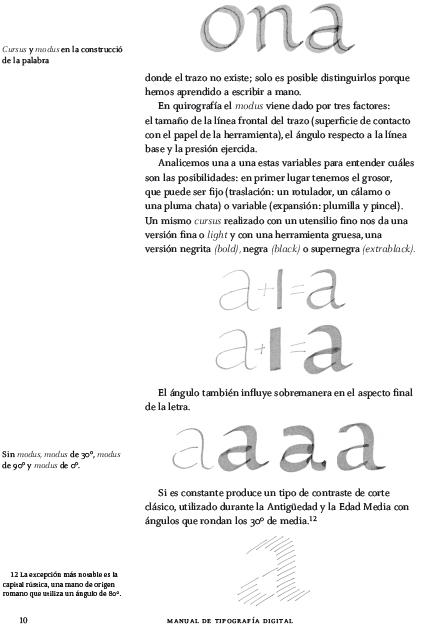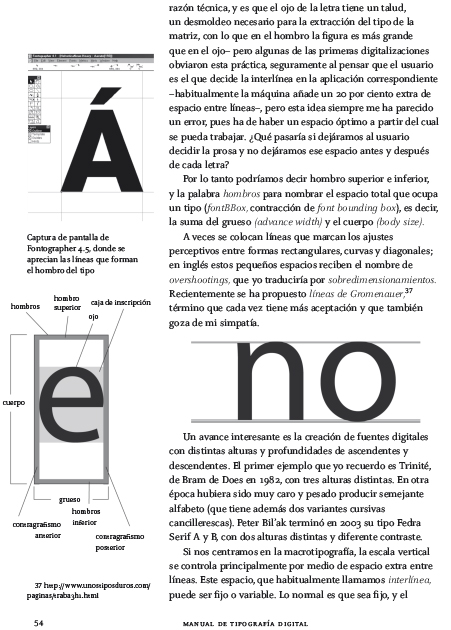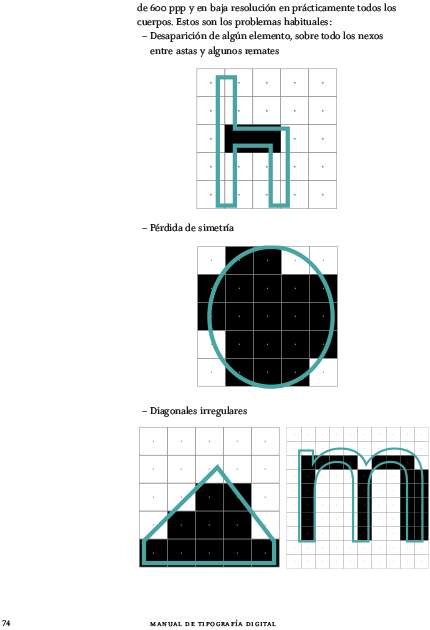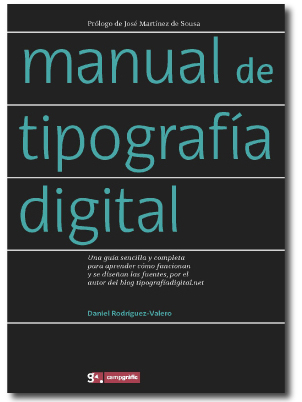
De un tiempo a esta parte la disponibilidad de textos sobre tipografía en castellano ha aumentado de forma significativa: manuales de uso, ensayos teóricos, descripciones históricas… pero cada vez que un nuevo título aparecía en el mercado siempre me quedaba la misma sensación: más de lo mismo. Siempre acababa echando en falta alguna obra que se metiera a fondo con la tipografía digital, la tipografía que surge con el ordenador personal a mediados de los años 80 del siglo pasado. Bien, pues esta obra ya la tenemos en nuestras manos. Su editor es la editorial Campgràfic, no podía ser otra, y su autor Daniel Rodríguez-Valero, doctor en Bellas Artes por la Universidad de Barcelona, profesor de diseño gráfico en la Universidad de Alicante y creador del imprescindible blog sobre tipografía tipografiadigital.net.
Bajo el título de Manual de tipografía digital y tras el prólogo del maestro José Martínez de Sousa siempre acertado y certero, Daniel abarca un amplio espectro de temas estructurados en dos partes principales: la primera en la que bajo el título de Cómo funciona la tipografía digital, el autor repasa los principales componentes de una fuente tipográfica digital tanto los visibles, los glifos, como los invisibles, el código que los acompaña y que, a fin de cuentas, es parte esencial de la fuente ya que esta no deja de ser un programa de software como de manera didáctica y amena queda descrito en este apartado.
Un apartado que comienza con consideraciones y apuntes clásicos sobre la construcción de una letra, sus clasificaciones y usos y que termina con un muy interesante apartado sobre el aspecto legal de la creación tipográfica, un tema que como hemos podido constatar en persona es recurrente en todos los que se aventuran a crear una fuente digital. En este sentido pensamos que es todo un acierto del autor tocar este tema.
Entre medias nos encontramos con aspectos básicos como la codificación o el dibujo vectorial hasta un extenso repaso por los diferentes formatos en los que se pueden presentar las fuentes tipográficas digitales, algo que creo no es muy conocido más allá de que Opentype es compatible con Mac y Pc.
La segunda parte del libro Cómo crear una tipografía digital, trata del aspecto práctico de la creación de una fuente digital. Empezando por el diseño, siguiendo por la producción y terminando en la distribución el autor cubre todas las etapas necesarias para un proyecto de estas características añadiendo una parte muy novedosa y práctica que tiene que ver con el análisis y posicionamiento del producto que queremos crear. Unas nociones de marketing y branding aplicadas a la creación de tipografías que pienso que son sumamente interesantes y que aportan una visión que hasta ahora yo he echado en falta en los textos publicados al respecto.
Entre los contenidos de esta segunda parte también tenemos que destacar la parte dedicada al dibujo de los glifos, los ajustes ópticos que deberemos aplicar y unas nociones imprescindibles si lo que pensamos es crear una familia con diferentes variables.
Tengo que destacar también el tono general del libro, ameno, práctico y en ocasiones con toques de humor que acerca mucho al autor a sus lectores y convierte una lectura que en ocasiones podría resultar tediosa en otra muy fácil de seguir, y lo que es más importante comprender.
En este sentido reseñar asimismo el esfuerzo de Daniel por encontrar vocablos en castellano a una práctica dominada por el inglés y que poco a poco ha ido ocultando una rica tradición que el autor recupera y comparte con sus lectores.
En definitiva, por mi parte señalar que es el libro que estaba esperando sobre tipografía digital, que viene a cubrir un hueco evidente en la literatura disponible y que, con toda seguridad, se convertirá en un título de referencia tanto en el mundo profesional como educativo.
Manual de tipografía digital
Daniel Rodríguez Valero